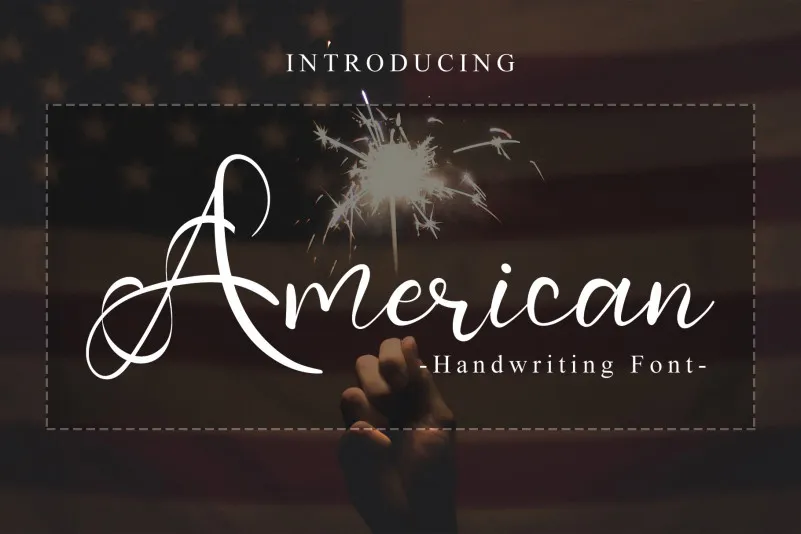
American Font – Download Grátis
Esta é uma fonte escrita a mão única e elegante. Ela se destaca por sua personalidade sofisticada, perfeita para projetos que precisam de um estilo único e autêntico, como convites de casamento, cartões de agradecimento, festas de aniversário, cartões de boas-vindas, logotipos ou qualquer outro tipo de design que deseja personalizar. Através deste fonte, você pode enriquecer seu trabalho com um toque delicado e autêntico, tornando-o ainda mais especial. Ela foi criada pelo Erik Studio, uma equipe experiente na criação de fontes escritas a mão, conhecendo bem o poder da personalização única em projetos gráficos. Ela é perfeita para quem busca manter um toque personalizado e delicado em suas criações digitais. É uma escolha ótima para quem deseja dar vida aos seus designs com uma escrita a mão única que combina elegância e originalidade, tornando-a uma excelente opção para designers apaixonados por criar um design único e autêntico.